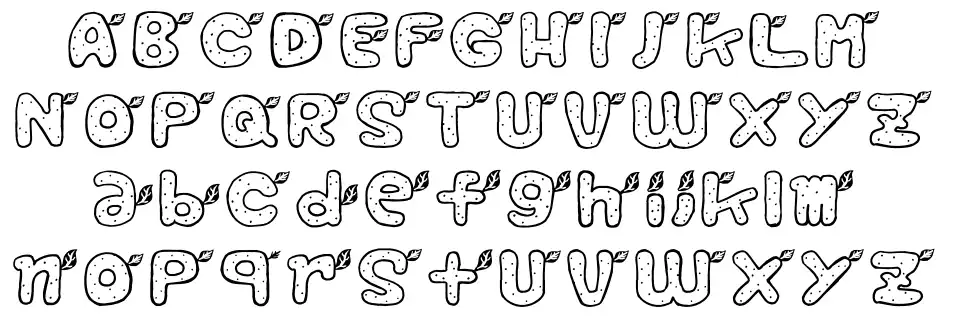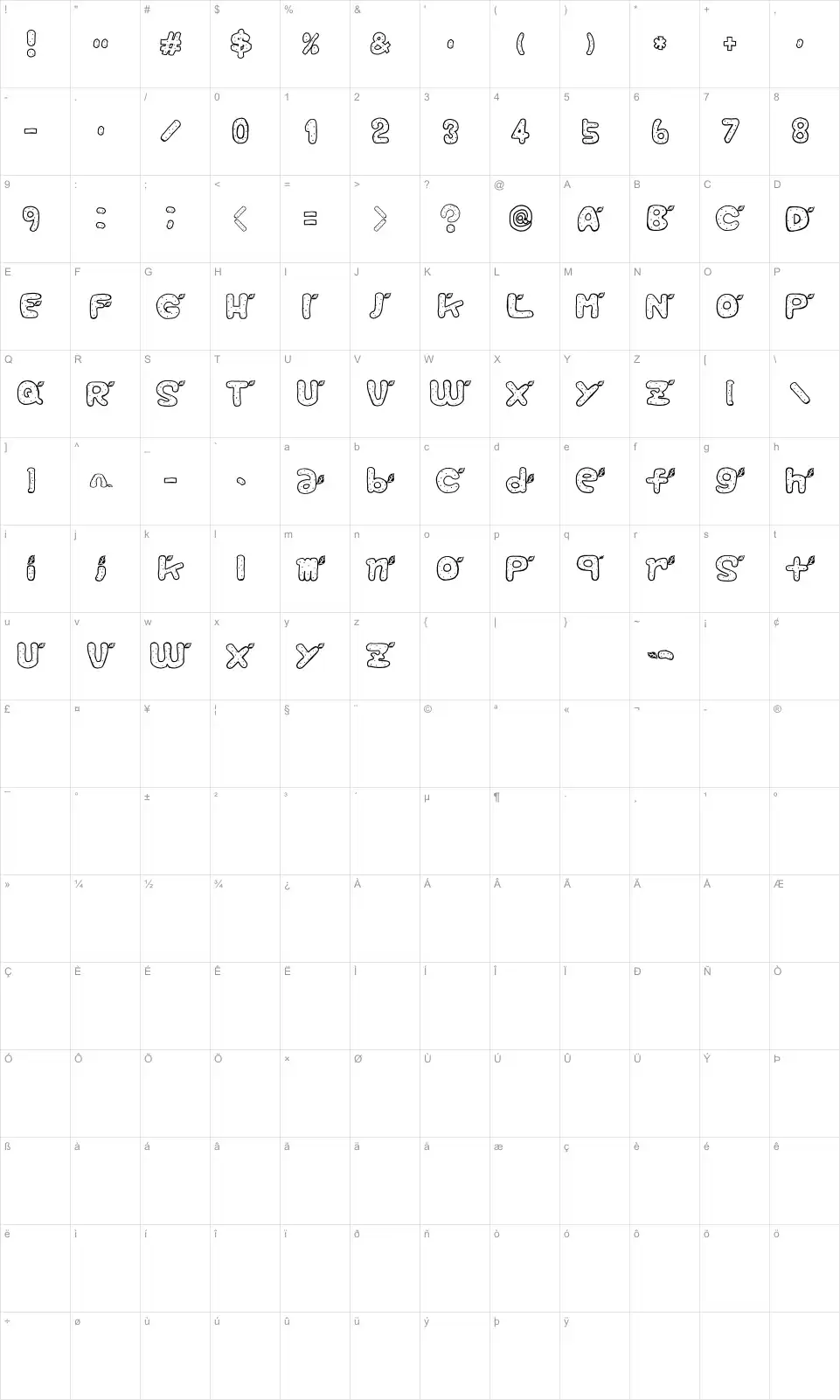
A fonte Reaf Font, criada pelo designer Shinji Hamada, é perfeita para aqueles que procuram um visual único e charmoso para seus projetos. Se você está buscando essa fonte incrível, aqui está uma ótima notícia: você pode agora descarregar ou gerar uma pré-visualização personalizada de texto diretamente do seu site, para ter uma ideia do como a fonte se destaca. Reaf é uma fonte da categoria Fancy > Decorative, que traz um toque autêntico e moderno para qualquer texto. Adicionada em 11 de julho de 2022, já foram baixados mais de 3200 cópias dessa fonte de tamanho compacto, com apenas 34 KB. Com suas linhas elegantes e texturas vibrantes, você pode dar um toque especial ao seu design. Para conhecer ainda melhor a Reaf Font, visite o site do designer, onde você pode explorar mais detalhes sobre essa fonte única. Com licença gratuita e formato TTF, a fonte Reaf é uma opção perfeita para quem busca uma fonte versátil e charmosa. Descarregue-a hoje e dê vida à sua arte com esta fonte fantástica.
Categoria: Fancy › Decorative
Designer: Shinji Hamada